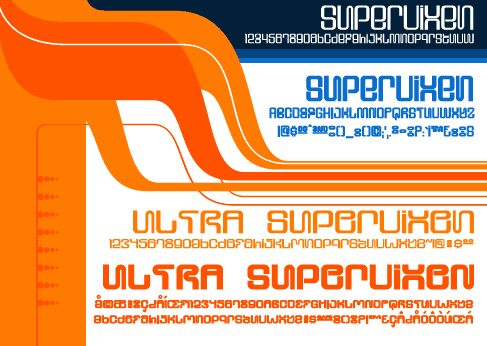
Supervixen od Font"a"licious Fonts to darmowy, futurystyczny krój displayowy z eleganckim techno-klimatem późnych lat 90. Litery są wysokie, delikatnie kwadratowe i opływowe, z zaokrąglonymi rogami i głębokimi prześwitami, co nadaje całemu projektowi płynny, syntetyczny puls, zamiast surowego, industrialnego wrażenia.
Dzięki temu Supervixen jest naturalnym wyborem na klubowe ulotki, okładki sci-fi, tytuły gier, identyfikację marek technologicznych oraz nagłówki stron, gdzie darmowy font potrzebuje nuty retro-futurystycznego połysku. Sprawdza się najlepiej w krótkich formach, zwłaszcza w napisach tytułowych i logotypach, ponieważ powtarzalny pionowy rytm i obła geometria robią największe wrażenie.